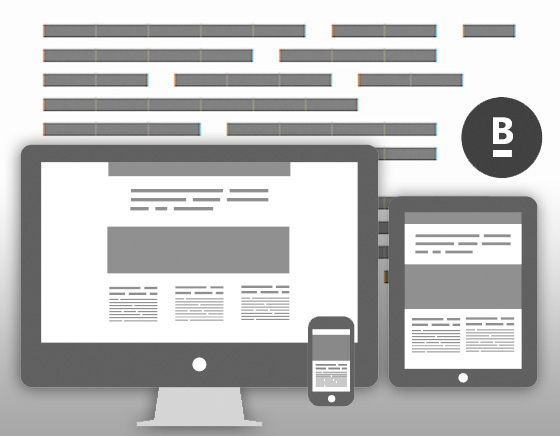
Si vous travaillez dans la PAO, le graphisme ou que vous devez régulièrement faire des mises en page pour vos clients, vous avez sans doute souvent eu recours au classique générateur de « faux textes » le fameux « Lorem Ipsum« …
Bye bye Lorem Ipsum
Grâce à lui, vous n’avez donc pas besoin de copier coller un texte quelconque pour remplir vos colonnes et ainsi pouvoir mettre en page vos documents, seulement voilà les personnes travaillant avec des langues non latines vont rencontrer inévitablement quelques soucis de mise en page avec « Lorem Ipsum » qui est de fait incompatible, pour pallier ce problème le studio norvégien Dinamo Services a imaginé Blokk Font une police de caractère bien singulière.
Proposée gratuitement au format TrueType – .TTF – mais aussi en webfont et compatible sur Mac et PC, celle-ci va vous permettre de générer de faux textes graphiques, sortes de blocs qui vont simuler l’espace occupé par un texte qu’il soit latin, hébraïque, arabe ou encore chinois. Cette vision plus graphique des faux textes indispensables pour tous travaux de PAO, vous fera très vite oublier le désormais très ordinaire « Lorem Ipsum » et surtout vous fera gagner en productivité.